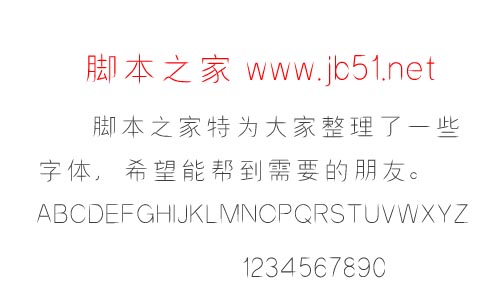
邯鄲雙劍細(xì)體是邯鄲字庫(kù)推出的一款非常漂亮的藝術(shù)字體,風(fēng)格比一般的字體更有特色,連貫字跡顯得干練而不凌亂,清新簡(jiǎn)明,具有很好的視覺(jué)感,適合應(yīng)用于藝術(shù)設(shè)計(jì)、平面宣傳設(shè)計(jì)、網(wǎng)頁(yè)設(shè)計(jì),書(shū)法字帖等領(lǐng)域,歡迎喜歡邯鄲雙劍細(xì)體的朋友前來(lái)下載使用。